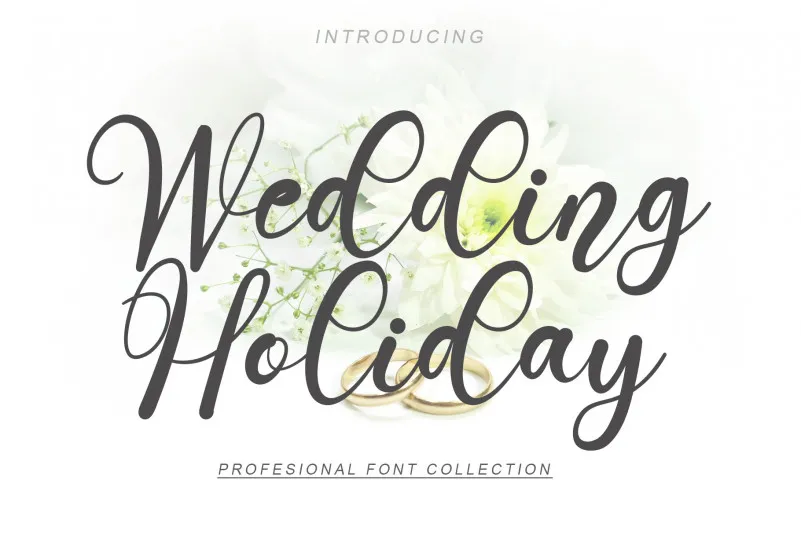
Wedding Holiday Font – Download Grátis
A fonte “Wedding Holiday” é uma elegante fórmula de escrita manuscrita que mantém seus influentes desenhos cáligraficos ao mesmo tempo modernos e frescos. Suas linhas fluídas e delicadas se adaptam perfeitamente a qualquer projeto, seja um card de convidados, cartão de Natal ou até mesmo um registro de casamento. Ideal para quem busca uma mão escrita única que transmita beleza e elegância, essa fonte é perfeita para levar seus trabalhos aos patamares mais altos. É como uma carta de amor para qualquer projeto onde você precisa manter seu design autêntico ao mesmo tempo em que se move com facilidade no cotidiano atual. Neste blog de recursos gráficos, estamos certos de que essa fonte é uma excelente adição a sua biblioteca pessoal.